단팥빵처럼 통실통실한 그녀들의 폰트 이야기
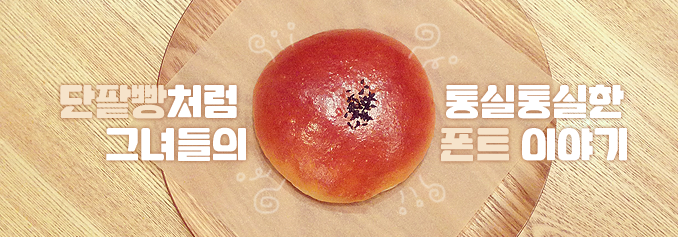
인터뷰 요청에 온 얼굴 근육이 다 함께 합창하는 것 같은 표정을 지으며 두근두근해 하는 1년차 디자이너. 서체 디자인과 관련해서는 누구보다 진지한 열정을 보여주는 2년차 디자이너. 아직 어리다고 할 지는 모르겠지만, 인터뷰를 해 보니 단팥빵 속 앙금처럼 내실있게 꽉 찬 그녀들의 이야기를 들어볼 수 있었다. 이름만 들어도 달착지근하고 포근해지는, 그 이름도 ‘단팥빵’이라는 서체와 함께 폰트디자이너 2인을 소개한다.
두 분 안녕하세요, 자기소개 부탁드립니다.
김수진 : 안녕하세요. 산돌커뮤니케이션 커스텀 폰트팀 김수진입니다. 단팥빵 서체 기획을 담당했습니다.
안효진 : 단팥빵 서체 제작을 맡은 커머셜 폰트팀 안효진입니다. 반갑습니다!
반갑습니다. 현재 하고 계신 업무를 소개해주시죠.
안효진 : 단팥빵 서체의 뒤를 이을 새로운 서체를 구상중입니다. (웃음)
김수진 : 최근 KT올레체Neo 프로젝트를 마무리했어요. 약 1년의 제작기간이 걸린 대규모 프로젝트였는데, 이번 2014 레드닷 디자인 어워드 서체 부문에 수상도 해서 매우 뿌듯했습니다.
▲ 수진씨가 참여한 KT올레체Neo서체의 웨이트별 모습
두 분의 인턴시절은 어떠셨나요?
김수진 : 2012년 7월부터 10월까지 인턴으로 근무했어요. 당시 인턴 프로그램이 따로 있었고, 사내에서 진행하는 한글 디자인 교육도 들었었죠. 1인 1개 신서체 개발이 당시 목표였는데, 완전한 서체는 아니어도 빈출자까지 제작할 수 있었어요. 기획과 디자인 컨셉을 잡고 제작을 진행하며 팀장님께 피드백을 받는 식이었죠.
안효진 : 저는 인턴기간이 3개월로 짧았어요. 바로 실전 업무에 투입되어 작업을 시작했죠. 한글날 행사에 참여한 덕분에 회사에도 금방 적응했고요. 인턴 시절 가장 기억에 남았던 때는 한 번 크게 울었던 날이에요. 제 머리 속에는 커다란 대작이 둥둥 떠다니는데 답답하고 잘 몰라서 터졌
던 눈물이었죠. 잘 하고 싶었던 마음이 컸나 봐요. (웃음)
김수진 : 저도 그런 경험이 있어요. 그래서 더 열심히 하게 된 것도 같고요.
단팥빵, 이 귀여운 서체의 시작은 어땠나요? 기획과정을 듣고 싶습니다.
김수진 : 신서체와 관련해서 아이데이션하는 과정이 있었는데 그에 맞춰 진행했던 주제가 ‘복고’였어요.당시 복고 열풍도 있었고 또 유행이란 건 돌고 도니까, 복고 컨셉의 폰트를 기획하게 됐죠. 인턴시절 기획했던 서체도 마침 복고서체여서, 자료 찾기도 수월했고 지금의 ‘단팥빵’이 탄생했어요.
기획에 있어 특별히 신경 쓰신 점이 있다면요?
김수진 : 평소 OEM(외부에서 의뢰를 받아 반제품이나 완제품 형태로 제작해 납품하는 형태)서체 개발을 주로 하다 보니, ‘글자의 균형과 비례를 맞춰야 한다’는 생각에 사로잡혀있었어요. 그걸 캐치하신 팀장님께서 ‘단팥빵 서체는 다듬고 정리하기보다 조금 더 풀어서 해보는 게 좋겠다’고 말씀해주셨죠. 균형이 맞지 않아도 그 만의 매력이 있는 서체고, 틀 안에 넣으려고 하기보다 강조할 부분은 크게 강조하는 게 어울릴 것 같다고요. 한 마디로 많이 건드리지 않길 바라셨어요. 건드리면 건드릴수록 애초 기획한 복고적이면서 단순한 그래픽 느낌이 살지 않더라고요. 단팥빵 서체를 보면 획의 굵기와 곡률이 글자마다 다른데, 완전한 균형을 추구하지 않은 사례에요.
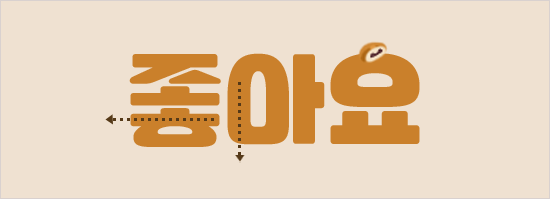
▲ ‘ㅎ’의 가로획과 ‘ㅇ’의 세로획에 굵기 차이가 있는 단팥빵 서체
디테일한 컨셉 결정이나 자료조사 등은 어떻게 진행하셨어요?
김수진 : 복고풍의 서체를 제작하기 위해선 옛날 자료들이 필요했어요. 옛 간판, 신문, 포스터, 패키지 등. 그 당시의 사회적 이슈나 배경에서 관련된 자료들을 모으고 마인드맵을 만들어 핵심 키워드로 컨셉을 도출했죠. 외부에서 리서치 할 경우에는 종로나 충무로 쪽을 찾아 다니며 사진도 촬영했고요. 요즘은 전자신문을 통해서 옛 기사들을 볼 수 있잖아요? 연도별로 신문 지면을 하나하나 살펴봤는데 피로회복제 광고, 분유 광고, 극장에서 상영하는 영화 포스터 등등 개성 있는 글자들이 참 많더라고요.
▲ 기획 단계에서 참고했던 그 당시 풍경을 담아낸 이미지들
서체의 모티브를 콕 짚어주신다면요?
김수진 : 60-70년대를 배경으로 하기 때문에 시대적으로 연상되는 느낌과 이미지에서 영감을 받았죠.그 중 가장 영향을 많이 받은 부분이 ‘스텐실’인데요. 당시는 인쇄술 발달 전이기 때문에 목판이나 활판인쇄로 글자를 찍어내는 경우가 많았어요. 그래서 옛날 글자들을 살펴보면 자소에 과감하게 도형형태를 쓰기도 했죠. 그걸 단순화 시켜서 한글에 접목해본 것이 단팥빵 서체입니다. 보면 ‘ㅅ’이나 ‘ㅈ, ㅂ’ 등이 굉장히 기하학적이에요.
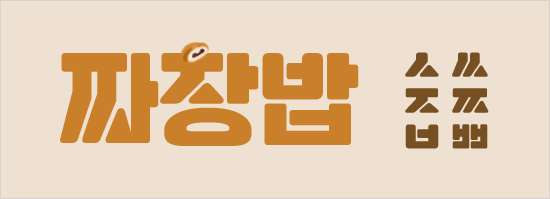
▲ 스텐실의 느낌이 묻어나는 자소들
단팥빵이라는 이름은 어떻게 탄생한 건가요? 정말 귀엽습니다.
김수진 : 처음 시안 작업을 했을 때 배가 고팠는지 딱 떠오른 문구가 ‘최고의 맛, 단팥빵과 모찌’였어요. (웃음) 근데 막상 그 문구를 보니 서체와 정말 잘 어울리는 거에요. 다른 분들께서도 ‘다른 이름으로 하지 말고 이대로 가자’ 하셨죠. 옛날 빵집 간판에서나 볼 법한 글자처럼, 옛날 향수를 불러일으키는 느낌을 줄 수 있어서 ‘단팥빵’으로 확정했어요.
굳이 ‘단팥’인 이유는 없을까요? 옛날 빵도 종류가 많잖아요. (웃음)
안효진 : 다른 빵보다 뻔질뻔질(?)하게 윤기도 나고 먹음직스러운 느낌이니까? 깨도 뿌려지고요. 단팥빵이 최고죠. (웃음)
김수진 : 굳이 말씀 드리자면 모든 사람이 좋아할 것 같은 빵이 ‘단팥빵’ 아닐까요? (웃음)
그럼 이제 효진씨께 바통을! 단팥빵 제작 과정을 간단히 알려주시겠어요?
안효진 : 일단 210자 정도 되는 빈출자를 제작하고 전체적인 느낌을 점검하며 한글 2,350자를 만들어요. 그리고 숫자, 영문, 기호 등을 추가 제작합니다. 그 후 한글과 영문, 숫자, 기호 등의 전체적인 조화를 위해 검수와 조판테스트를 여러 차례 진행해요.
그렇게 어느 정도의 시간이 걸리신 거에요?
안효진 : 올해 4월 말부터 7월 중순까지, 3개월 정도 걸렸네요.
김수진 : 다른 프로젝트에 비했을 때 단팥빵은 굉장히 ‘풀어놓은 프로젝트’였어요. 원래 가지고 있던 모듈의 특성을 그대로 가지고 오면서 약간의 밸런스만 맞춘 작업이었거든요. 하지만 밑바탕 글자가 몇 자 없는 상태로 시작했기 때문에 오래 걸릴 수 있었던 일을 효진씨가 빨리 한 셈이에요.
그렇군요. 작업 중 어려웠던 점이 있었나요?
안효진 : 단팥빵 서체를 제작하면서 여러 사람에게 많은 조언을 구했는데, 그러다 보니 여러 사람이 원하는 바가 모두 묻어난 듯한 느낌이었어요. 그래서 나중에는 수진 선배와만 의논을 하게 됐죠. (웃음)
김수진 : 어쩐지 어느 순간부터 제 자리에 계속 찾아오더라고요. (웃음) 또, ‘ㅇ’계열과 ‘ㅅ’계열 두 가지를 봤을 때 서로 다른 서체 같아서 고민했던 것도 기억나요. 하지만 이것도 매력이죠. 개성이 많이 담긴 거니까요.
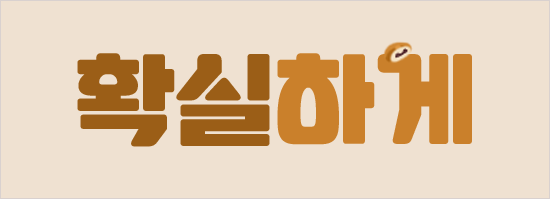
▲ ‘확’자와 ‘실’자를 보면 각각 단팥빵의 모양과 스텐실의 느낌으로 구분된다.
단팥빵 모듈에서 가장 눈에 띄는 점이 아마 ‘ㅇ’이 아닐까 싶은데요. 받침이 없는 글자의 ‘ㅇ’과 있는 글자의 ‘ㅇ’ 형태에서 고민하셨을 것 같아요.
안효진 : 아래 문구를 보면, ‘아’의 ‘ㅇ’부분은 아랫부분이 조금 각져 있지만 ‘앙’의 ‘ㅇ’은 그렇지 않죠. 받침이 없는 ‘ㅇ’에서는 아랫부분이 각진 것이 컨셉이에요. ‘ㅁ’같으면서도 ‘ㅇ’ 같은, 일반화되지 않은 컨셉이죠.
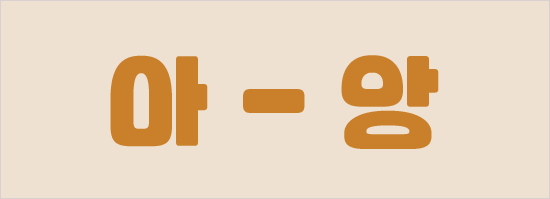
단팥빵 서체와 관련된 다른 에피소드도 말씀해주세요.
안효진 : 소문자에 대한 의견이 분분했던 알파벳 제작이 기억에 남아요. 틀에 꽉 찬 모듈이고 콘트라스트도 없다 보니 원체 굴곡이 많은 소문자는 공간도 부족하고 모양도 이상했어요. 결국 소문자 없이 가게 됐는데, 아마 회사 최초로 소문자가 없는 서체가 아닐까 싶어요.
김수진 : 또, 맨 처음 기획한 스텐실 느낌이 알파벳에서는 나지 않아서 처음 시안보다 많이 변경됐던 것 같아요.
안효진 : A, M, W, X등을 보시면 아시겠지만, 포인트를 특정 알파벳에만 줬답니다.
김수진 : 특히 M과 W자는 공간 확보를 위해서 획을 생략했어요. 단순화로 인한 특이케이스!
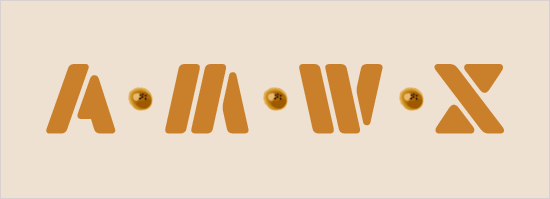
▲ ‘시각 삭제’ 원리가 적용된 알파벳 자소들
수진씨의 에피소드도 말씀해주세요.
김수진 : 저는 피드백을 주는 입장이다 보니 거의 서포트 역할만 했어요. OEM 작업을 진행 중이었고,중간 중간 작업물을 확인하고 의견을 주는 게 힘든 적도 있었죠. 하지만 지금 생각해 보면 기존 업무를 리프레시 할 수 있었던 게 단팥빵 작업이었어요. 그리고 효진씨에게 고마운 건 제가 요구했던 사항을 즉각 수정해줬다는 점이에요. 제가 굉장히 많은 사항을 요구했었는데 효진씨 작업 속도가 빨라서 바로 바로 수정해 오더라고요. (옆에서 엄지손가락 치켜드는 효진씨) 저도 그렇게 배워왔었고 직접 해봐야 느는 작업이란 걸 알고 있기 때문에 그렇게 요구하지 않았나 싶어요. 효진씨는 문제도 빨리 캐치하는 편이에요. 어쩔 땐 제가 놓치고 있었던 부분도 찾아와 물어보고요. 수동적으로 글자만 파생하는 것이 아니라 디테일하게 글자 한 자 한 자에 정성을 쏟았죠.
심혈을 기울여 만들어진 단팥빵, 어떻게 활용되면 좋을까요?
김수진 : 개성이 듬뿍 담긴 서체이다 보니 임팩트 있고 짧은 단어에 사용하면 효과적일 것 같아요. 방방 뜨지 않고 차분한 이미지에서 쓰여도 좋을 것 같고요. 전체적인 느낌이 밝고 귀엽고 올망졸망하지만 진지하고 무던한 글에서도 쓰이길 바래요.
안효진 : 제목용을 위해 만들어진 서체이지만, 10포인트 정도로 작게 써도 은근 예뻐요. 쓰시는 분들의 마음이기는 하지만 딱 봤을 때 엄청난 주목성을 가지고 있기 때문에 제작의도에 맞게 제목용으로 사용하시면 좋지 않을까요?
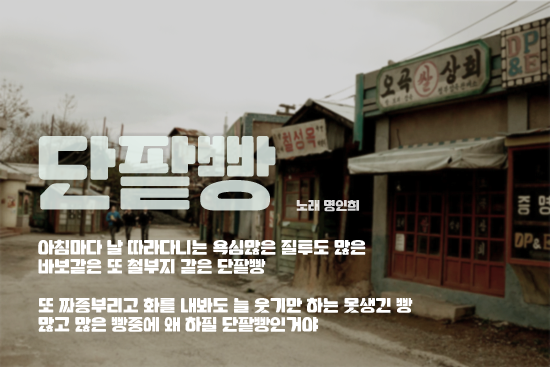
김수진 : 저도 그 책을 가장 처음 접했던 것 같아요. 영문 서체와 관련해서는 <좋은 디자인을 만드는 서른 세가지 서체이야기, 김현미>를 추천해요. 시대적인 정리가 잘 되어있어서 타이포그라피의 역사를 훑어볼 수 있는 책이거든요. 영문서체에 대해 아무것도 몰랐을 때 ‘알파벳의 형태가 이렇게 변모하고 이렇게 발전하는구나’를 쉽게 알 수 있었죠. 누구에게나 한 번쯤 소개해주고 싶은 책이에요.
두 분도 영향을 받은 서체나 서체디자이너가 있으시죠?
안효진 : Akzidenz Grotesk(악치덴츠 그로테스크)를 좋아해요. 서체가 못생겼다고 많이들 말하는데 제 눈에는 예쁘거든요. 헬베티카를 만드는데 기본이 되기도 했다고 해요.
김수진 : ‘아드리안 프루티거’가 제작한 유니버스 서체를 좋아해요. 최초로 활자 패밀리라는 표준 시스템을 만들었고 21개로 구성된 유니버스 팔레트는 지금 봐도 너무나 체계적이고 이상적이라고 생각해요.
▲ Akzidenz Grotesk
▲ 유니버스 서체 패밀리 중 일부